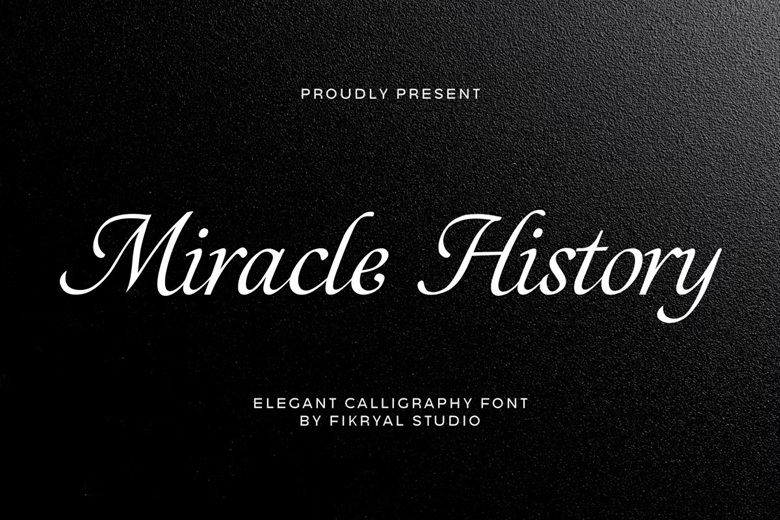
Font việt hóa Miracle History đẹp dành cho thiết kế
Miracle History là một kiểu chữ Serif cổ điển kết hợp với phong cách hiện đại, được thiết kế để gợi lại vẻ đẹp sang trọng và lịch sử của những ấn phẩm in ấn cổ điển, nhưng vẫn mang hơi thở đương đại. Font này mang lại cảm giác trang nghiêm, nghệ thuật và chuyên nghiệp – rất phù hợp với những dự án cần truyền tải sự cao cấp và hoài niệm.
Đặc điểm nổi bật của Font Miracle History
• Phong cách serif cổ điển: Font có các chân chữ (serif) sắc sảo, hơi kéo dài, giúp tạo cảm giác trang nhã và uy tín.
• Đường nét tinh tế, có độ tương phản cao: Các nét chữ được vẽ thủ công với sự tương phản rõ giữa nét dày và nét mảnh đặc trưng của những font in sách cổ xưa.
• Hơi hướng hoài niệm: Miracle History mang phong cách retro – classic, gợi nhớ đến các tiêu đề báo chí cũ, bìa sách cổ hoặc kiến trúc thời phục hưng.
• Việt hóa đẹp mắt: Font được việt hóa kỹ lưỡng, các dấu tiếng Việt được căn chỉnh chuẩn xác, không làm vỡ bố cục tổng thể của font.
Ứng dụng của Font Miracle History
Font Miracle History thích hợp với các dự án cần đến sự lịch thiệp, cổ điển và nghệ thuật, bao gồm:
• Thiết kế logo thương hiệu cao cấp: Phù hợp với các thương hiệu mang tính di sản, truyền thống, hoặc trong ngành thủ công mỹ nghệ, nghệ thuật, nội thất cổ điển.
• Tạp chí, bìa sách, tiêu đề in ấn: Rất lý tưởng cho các ấn phẩm xuất bản theo phong cách cổ điển hoặc mang yếu tố văn hóa, lịch sử.
• Bao bì sản phẩm thủ công, mỹ phẩm cao cấp: Tăng tính giá trị và sự tin tưởng cho sản phẩm thông qua kiểu chữ trang trọng.
• Poster nghệ thuật, triển lãm, thư mời trang trọng: Tạo cảm giác cao cấp, sang trọng nhưng vẫn gần gũi, dễ đọc.
Miracle History không chỉ đơn thuần là một font serif cổ điển, mà còn là sự kết hợp giữa lịch sử, thẩm mỹ và kỹ thuật hiện đại. Font này sẽ giúp bạn kể những câu chuyện thiết kế một cách đầy chiều sâu và phong cách, đặc biệt nếu bạn đang hướng đến sự sang trọng, hoài cổ và chuyên nghiệp.